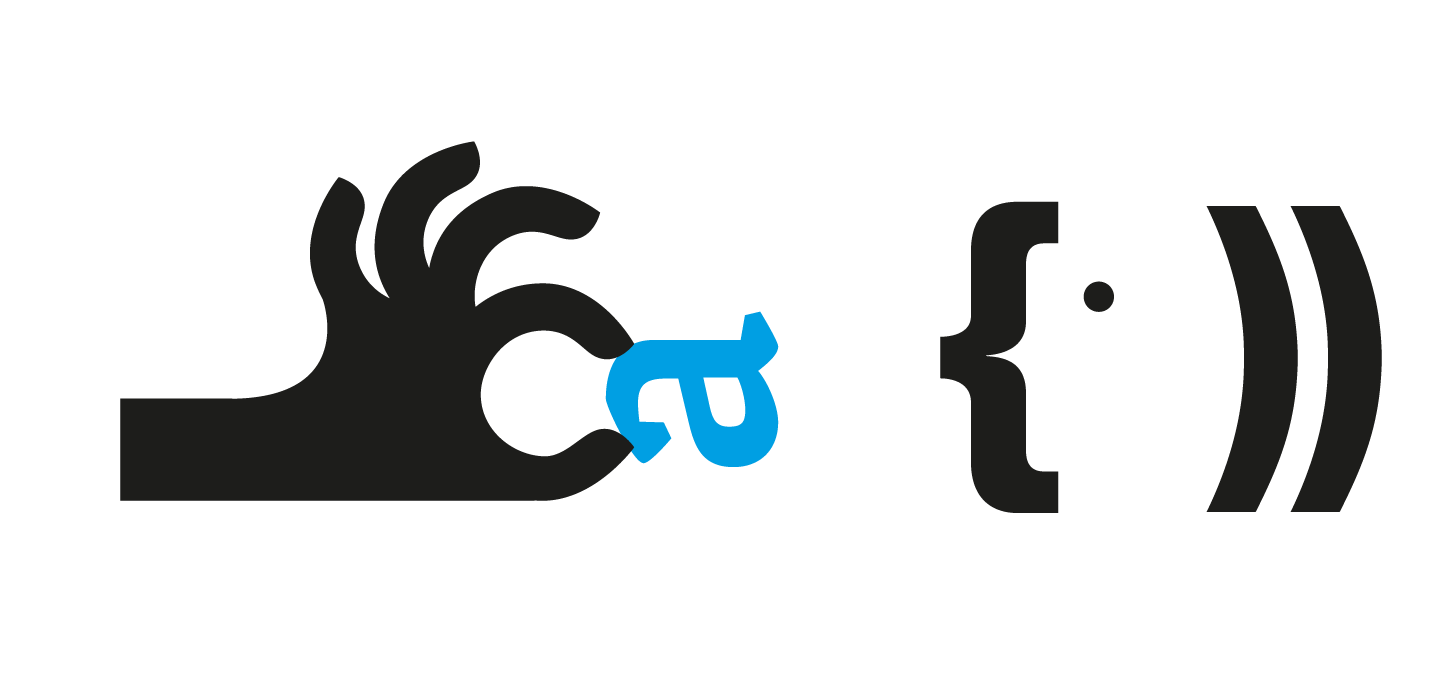
Puerto Sauce
Puerto Sauce es una tipografía que nace desde lo más personal: mi ciudad, Juan Lacaze. Es el resultado de mirar con otros ojos lo que siempre estuvo ahí —las fábricas, el puerto, el viento, los barcos pesqueros, las calles de tierra, la gente trabajadora— y traducir todo eso en letras.
Quise que esta tipografía tuviera esa mezcla tan característica del lugar: lo estructurado de lo industrial y lo orgánico del entorno natural. Las rectas marcan lo firme, lo construido, la historia de la ciudad obrera. Las curvas, en cambio, traen el movimiento del agua, lo artesanal, lo humano. Esa dualidad recta y curva, técnica y emocional— fue el eje principal de todo el diseño.
Cada letra tiene algo del puerto, del río, de los galpones, del viento que nunca deja de soplar. No busqué que fuera perfecta, sino que tenga identidad, que se sienta real. Como si estuviera dibujada por alguien que vive ahí, con las manos marcadas por el trabajo, pero con la sensibilidad para ver la belleza en lo cotidiano.
Trabajar en esta tipografía fue también una forma de volver a conectarme con el lugar que me vio crecer. De entender que el diseño no está solo en los grandes conceptos, sino también en lo que uno conoce de cerca.
Porque entendí que diseñar no es solo hacer algo lindo: es decir algo, es dejar algo. Y si esta tipografía transmite aunque sea un poco de lo que significa mi ciudad para mí, entonces ya cumplió su objetivo.
Matías Mayo
Nusa
Nusa esa una tipografía basada en registros y memorias de pueblos charrúas originarios del Río de la Plata. Busca promover una recuperación gráfica de expresiones artísticas y símbolos de resistencia. Su principal inspiración proviene de los tatuajes con líneas azules hechos a mujeres charrúas, y del juego de cartas de lonja quemada de Laureano Tacuabé.
Es una sans serif con un intencional cambio de peso en sus terminaciones, compuesta por trazos firmes y secos que simulan los tallados indígenas en sus instrumentos de caza. Comunica fuerza, solidez e identidad.
Actualmente Nusa cuenta con una versión regular acompañada de 4 dingbats y 24 pictogramas capaces de escribir a la lengua castellana, y a aquellas pocas palabras existentes en lengua charrúa y chaná.
Iara Carabajal
Orientala
Orientala revive la caligrafía fundacional de Edward Johnston con un giro de contraste invertido -horizontales gruesas y verticales finas- que crea una tensión surrealista pero equilibrada. Fusiona la calidez humanista con la disrupción vanguardista.
Nacida del deseo de deformar la tradición, Orientala hace un guiño al legado de Johnston al tiempo que abraza lo insólito, como un fallo caligráfico en el tiempo.
Dogma 580
La tipografía no puede ser solo comprendida desde su formalidad, debe trascender en mucho los límites de lo visual y debe ser anclaje natural de lo conceptual, manifestación cultural con todo el peso que ese rol conlleva y con todo el significado que esa condición traslada a los productos tipográficos.
Con esta apertura se presentaba el documento Dogma 580, que proponía una producción tipográfica atravesada por una fuerte impronta ideológica.
Fuerte Type
Fuerte es un estudio independiente de diseño tipográfico con sede en Dubái (EAU) y Colonia (Uruguay), fundado por Fermín Guerrero.
Nos dedicamos al desarrollo de tipografías cuidadosamente elaboradas, con un fuerte atractivo gráfico, para ayudar a los diseñadores a crear experiencias visuales memorables. Nuestros proyectos combinan la precisión técnica y óptica del diseño tipográfico con conceptos arraigados en nuestra práctica del diseño gráfico.
Underground
Surgió como un canal de distribución comercial alternativo a TipoType distribuyendo sus tipografías en la plataforma MyFonts.